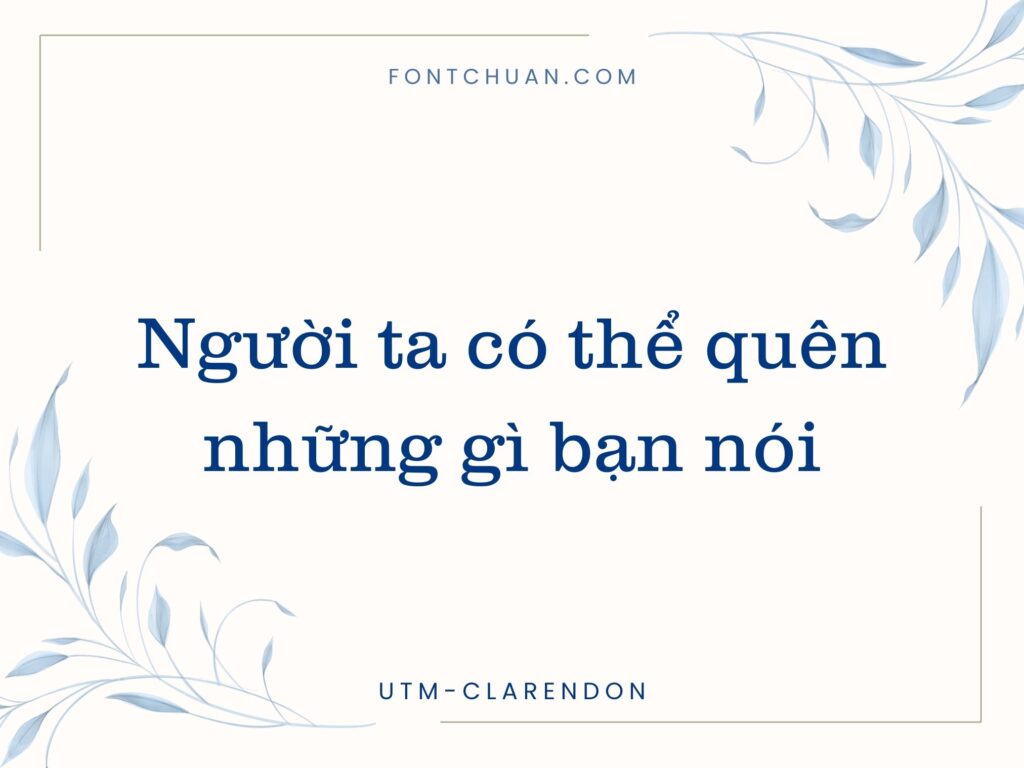
Font UTM Clarendon Việt Hóa
UTM Clarendon là phiên bản Việt hóa của font chữ Clarendon, một kiểu Font Slab Serif cổ điển được thiết kế bởi Robert Besley và phát hành lần đầu vào năm 1845. Font này nổi bật với các ký tự có chân dày và đường nét mạnh mẽ, tạo cảm giác vững chắc và đáng tin cậy và mang phong cách Font Vintage đặc trưng, gợi nhớ đến những thiết kế in ấn cổ điển thế kỷ 19. Phiên bản Việt hóa đã được thực hiện bởi Unicode Thiên Minh, hỗ trợ đầy đủ tiếng Việt cùng hơn 100 ngôn ngữ khác. Đây là một trong những font được cộng đồng thiết kế sưu tầm và chọn lọc nhằm đáp ứng nhu cầu đa dạng trong thiết kế.
UTM Clarendon có cấu trúc chữ với các nét dày và chân chữ rõ ràng, tạo nên sự nổi bật và dễ đọc. Font này phù hợp cho các ứng dụng như thiết kế tiêu đề, logo, biển hiệu và các ấn phẩm in ấn yêu cầu sự mạnh mẽ và chuyên nghiệp. Các ngành nghề như quảng cáo, giáo dục, công nghệ và bất động sản có thể tận dụng UTM Clarendon để tạo điểm nhấn độc đáo trong thiết kế.